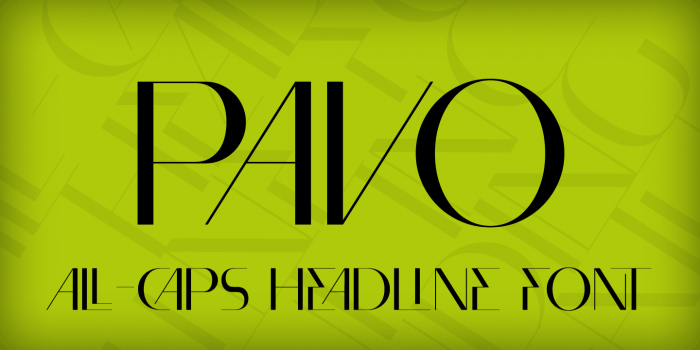
Auch wenn ich es rein grundsätzlich toll finde, wenn Menschen Schriften schaffen - aber sorry: ich kann mir aufgrund diverser ziemlich unleserlicher Buchstaben (E und F sind m. E. völlig unmöglich) keine Anwendung dafür vorstellen ... außer vielleicht als Wortmarke, in denen aber viele Buchstaben nicht vorkommen dürfen. Schade!
Erstmal Gratulation dazu, eine Schrift entworfen zu haben, die noch dazu gleich mit OpenType-Features bestückt ist. Zum Aussehen: Erinnert mich an den … wie sag ich das jetzt … extremkonstruktivistischen Stil, der gerade so trendy und hip ist. Eine der angesagtesten Foundrys in diesem Bereich ist im Moment Ten Dollar Fonts
Was mir persönlich bei der Pavo aufgefallen ist und nicht so gut gefällt, ist das S, das mir im Zusammenhang mit der Kantigkeit des E oder F zu rund ist. Auch ist die Rundung etwas zu weit unten, da sitzt es etwas zu sehr auf dem Popöchen.
Ich kann mir aber die Pavo gut in jedem Avant-Garde-Fashion-Zusammenhang vorstellen.
Fazit: Nicht entmutigen lassen durch etwaige Kritiken, weiter machen.
PS: Ein guter Weg, seine entstehende Schrift von Typedesignern und -experten bewerten zu lassen und schon vor Veröffentlichung zu optimieren, ist, sie im Forum Critique auf Typophile vorzustellen. Typedesigner wie Nick Shinn, Nick Cooke und andere geben dann hilfreiche Tipps, wie die Schrift noch besser aussehen kann.
Generell  gehört die Pavo ja in die Klasse der Headline-Schriften bei denen ein Gestaltungsprinzip maßgeblich ist und nicht klassischerweise das handschriftliche Schreiben. Sie steht damit in Tradition zum Beispiel mit der Avant Garde oder sogar ein bisschen den Experimenten eines Wim Crouwel. Und das sie nicht »everybody’s darling« werden wird ist mir durchaus bewusst. Muß sie aber auch nicht. Aber immerhin fand die Jury beim call-for-type Wettbewerb sie würdig.
@Schwalbenkoenig: Danke für den Hinweis zu typophile.com. Die ersten Entwürfe zur Pavo sind schon ein bisschen älter und damals hatte ich das Forum bemüht und ein paar Tipps berherzigt. Die critique section ist wirklich toll!!!